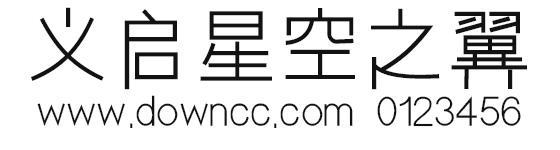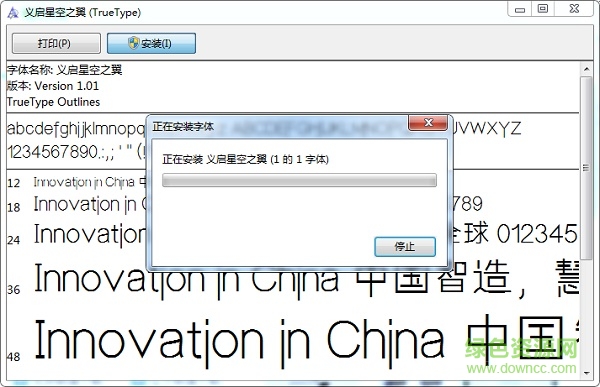
義啟星空之翼字體是一個ttf格式的電腦字體文件。小編為大家提供的這款字體可設(shè)計廣告、商業(yè)logo標識等。字體美觀,可以在photoshop、word文件中打開使用。
中文名稱:義啟星空之翼
義啟星空之翼字體有一種星空之翼的意境,字體的整體效果非常美觀,能夠適用于廣告設(shè)計、名片設(shè)計、包裝印刷、產(chǎn)品設(shè)計等領(lǐng)域喜歡這款字體的朋友快來綠色資源網(wǎng)下載體驗吧!